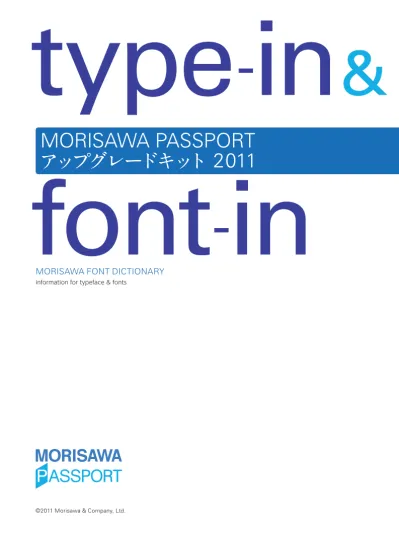
type-in&font-in 2011
MORISAWA FONT DICTIONARY information for typeface & fonts
MORISAWA FONT DICTIONARY
information for typeface & fonts
MORISAWA PASSPORT アップグレードキット2011 の特徴 リリース以 来 7 度目となる「MORISAWA PASSPORTアップグレードキット 2011」。本年度も、一層充実した内容でお届けします。 モリサワフォントの新書体は、新しい明朝体「黎ミン」をはじめ、かな書体「カモレモ ン」「カモライム」「欧体楷書 藤かな」、そして「くいこみ数字 縦」。 「黎ミン」は、これまでのモリサワのラインナップにはなかったモダンな明朝体で、シ ンプルで親しみやすい表情と、横組みにも使いやすい広めのフトコロをもっており、 モダンなゴシック体とも親和性が高いのが特長です。この「黎ミン」に横画などを 段階的に変化させた「黎ミンY10」「黎ミンY20」「黎ミンY30」「黎ミンY40」を 加えた、5ファミリー・34 書体で「黎ミングラデーションファミリー」を構成。紙だけ でなく、近年、高いクオリティが求められるデジタルデバイスでの利用など、明朝体 の可能性を大きく広げます。 アップグレードキット2010から提供が開始された、大日本スクリーン製造株式会 社のヒラギノフォントにも新書体が追加されました。大きな字面でくっきりと、はっ きりと見せる「ヒラギノUD角ゴ F」4 書体と、金属活字由来のクラシックなかなが 特徴的な「ヒラギノ角ゴオールド」4 書体の 2ファミリー・8 書体です。 そして、今回のアップグレードキットからは株式会社タイプバンクのフォントが加わ ります。その数は“つたわるフォント”の名称で知られるUD 書体・全 15 書体、そ して、パッケージの成分表記などに便利な、長体での使用を前提としたゴシック体 「TBゴシック for コンデンス」全 15 書体の計 30 書体にも上り、昨年に引き続き、 ブランドを超え、価値あるフォントを収録しています。 さらに魅力あるフォントが加わったMORISAWA PASSPORT。 ぜひご活用ください。 企画:株式会社モリサワ  編集・制作:有限会社フレスコ┼ MFDプロジェクト  デザイン:坂野公一[welle design]
「黎ミン」の開発背景
現在、私たちは印刷された紙の上の文字だけでなく、パソコンや 携帯電話、TV、屋外や社内の案内板など、画面に表示された文 字からも多くの情報を取得するようになりました。いまや、紙の上 の文字よりも、ディスプレイ上の文字に接する時間のほうが多いと さえ言われています。 こうした流れのなか、現代のニーズに合った明朝体のひとつの応 えとして誕生したのが「黎ミン」です。では、具体的にそのデザイ ンの特徴を紐解いてみましょう。 まず縦組みでも横組みでも、しっかりとした文字のラインが浮き上 がるよう、かなの字幅の差を極力おさえていることが挙げられます。 これまでの明朝体は、縦組みでの流れを意識してデザインされた ものが多く見られましたが、「黎ミン」では横組みでも、縦組み同様 に読みやすい設計になっています。 さらに、文字のフトコロを広く、大きく取ることで1 字 1 字の視認性 を大幅に向上させ、句読点やカギ括弧などの約物がかすれて見 えなくなることがないよう、太く、メリハリのついたデザインになって いることもポイントです。このような文字の設計は、高齢化などの 社会の流れにともなって変化する“文字の見やすさへのニーズ” に応えるものと言えるでしょう。
左:太ミンA101 中:黎ミン L 右:リュウミン L-KL
「黎ミン」の特徴
「黎ミン」の特徴はなによりも、シンプルで親しみやすいモダンな明 朝体であることです。「秀英明朝」や「リュウミンオールドかな」と いったオールドスタイルの明朝体のように、文字そのものが強い デザインイメージをともなうタイプの書体ではありませんが、クセ のないニュートラルなイメージこそ「黎ミン」の強みであり、どんな 状況でも使いやすい、その柔軟性を生み出す源と言えます。 そして、モダンな明朝体というこれまでのモリサワフォントにはなか ったカテゴリの書体が誕生したことで、「ゴシックMB101」や「ネ オツデイ」などのゴシック体とも、違和感なく組合せることができる ようになりました。横組みでもすぐれた可読性を発揮する「黎ミ ン」は、明朝体との組合せが難しかった「新ゴ」ともバランスよく組 合せることができます。モダンなゴシック体にあわせる明朝体の 選択に頭を悩ませる必要はありません。 「黎ミン」は、L、R、M、B、EB、H、EH、U の 8ウエイトを備えてい るので、すっきりと読ませたい本文やキャプションから、見出しやキ ャッチ、タイトルまであらゆるシチュエーションで活用することがで きます。いま、「リュウミン」や「太ミンA101」で組んでいる文字を 「黎ミン」に変えてみてください。「黎ミン」が持つニュートラルな たたずまいを感じることができるはずです。
青:黎ミン L 赤:リュウミン L-KL 「黎ミン」は、「リュウミン」に比 べて、字面が正方形に近く、括 弧類や約物もやや太めにデザ インされています 青:黎ミンY20 B 赤:UD 黎ミン B より文字の読みやすさ、見やす さを重視する必要があるときの ために、「UD 黎ミン」は用意さ れています。「UD 黎ミン」では、 文字の視認性を高めるために、 本来のデザインから欧文イタリ ックの角度や一部の文字のか たちを変更しています